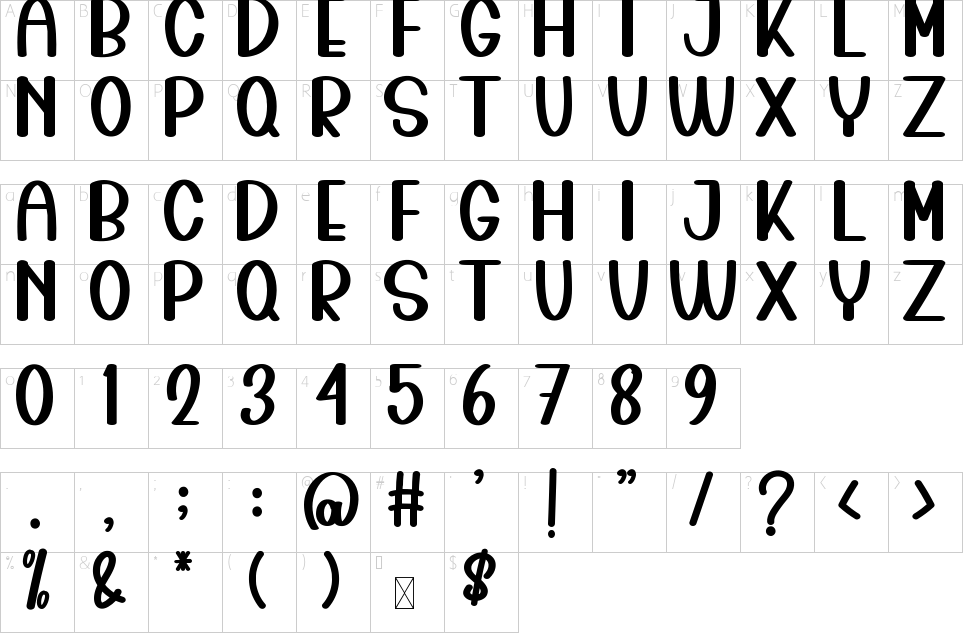
A fonte Pink Baby é uma criação suave e encantadora, perfeita para criar um ambiente alegre e divertido em projetos, desde anúncios até cartões de aniversário. Desenvolvida pela InermediaSTUDIO, esta fonte colorida e vibrante é uma excelente opção para aqueles que desejam adicionar um toque especial a seus materiais digitais, especialmente projetos destinados a crianças. Seu design é uma graça para os olhos e certamente fará seu público alvo sorrirem. É uma ótima opção para quem busca uma fonte de estilo infantil, leve e de bom gosto, que certamente não ficará desatualizada, pois é uma fonte gratuita. Seja para o seu próximo projeto, experimente Pink Baby e admire a diversão que ela traz.